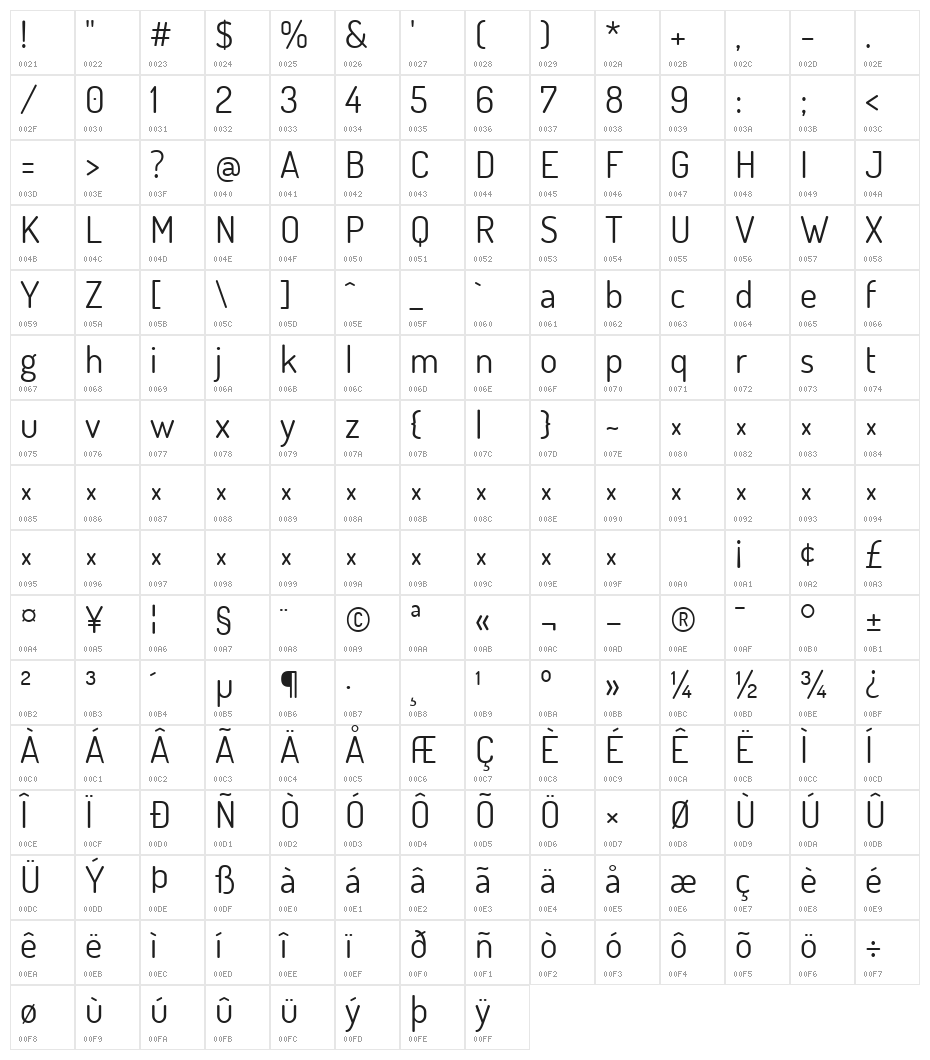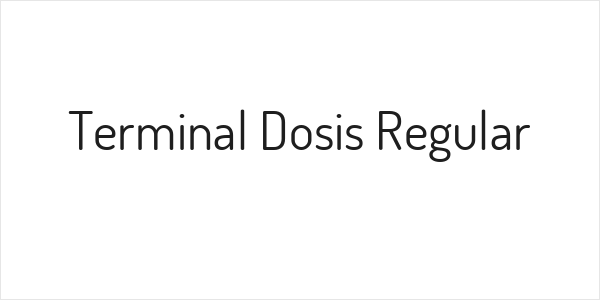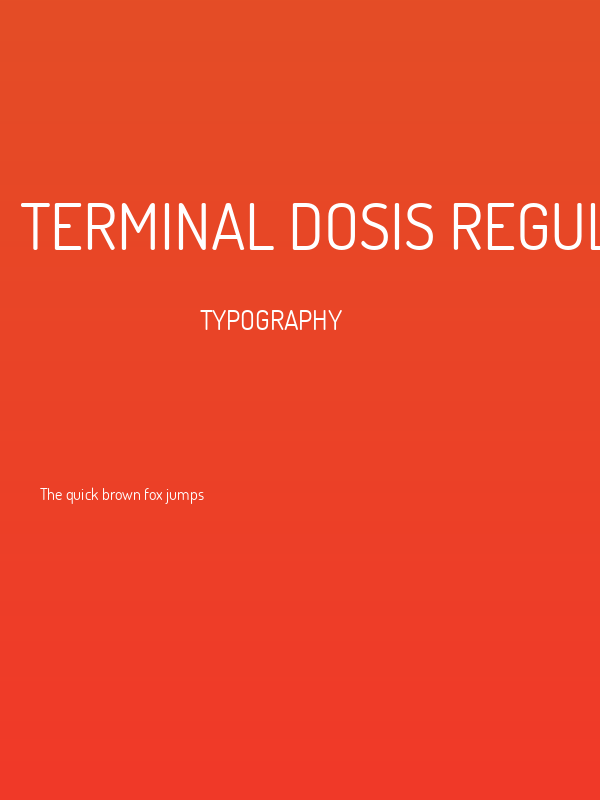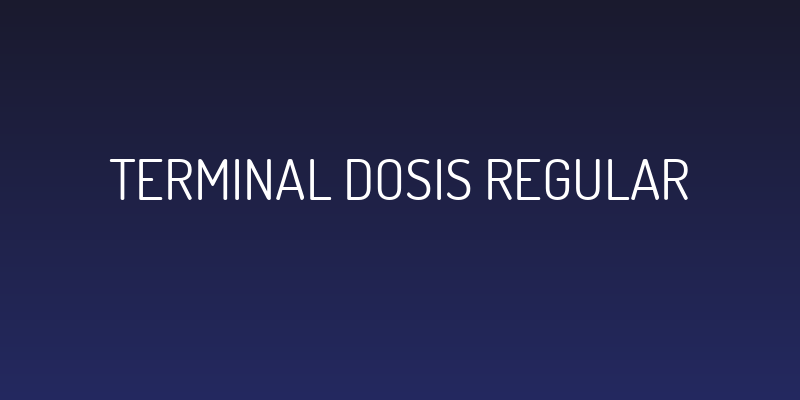
Terminal Dosis Regular Font
✎ Sans Serif
| حالة الاستخدام | Headlines, Body text, Logos |
| مشاريع مقترحة | Ideal for web design, app interfaces, branding, and advertising materials where a modern and friendly appearance is desired. |